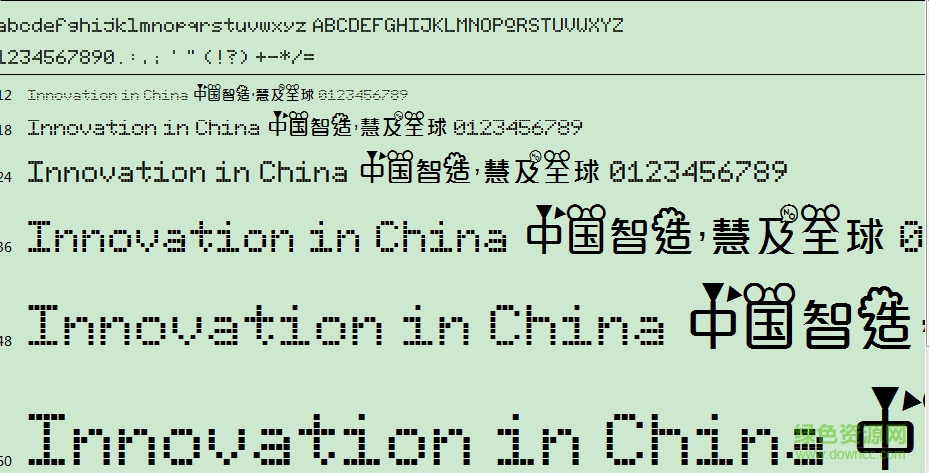
以愛(ài)之名字體是一款非常特色的藝術(shù)字體,這款字體中帶來(lái)各種漂亮的圖案,看上去非常的浪漫,喜歡的朋友不妨來(lái)綠色資源網(wǎng)下載吧!
在愛(ài)情里,很多為對(duì)方所做的事情,所準(zhǔn)備的禮物,都是以愛(ài)之名為出發(fā)點(diǎn)的,這款以愛(ài)之名字體也是基于這樣的理念設(shè)計(jì)的,哲人說(shuō),愛(ài)ta,就帶ta去扯證吧,給ta一個(gè)白紙黑字的承諾。